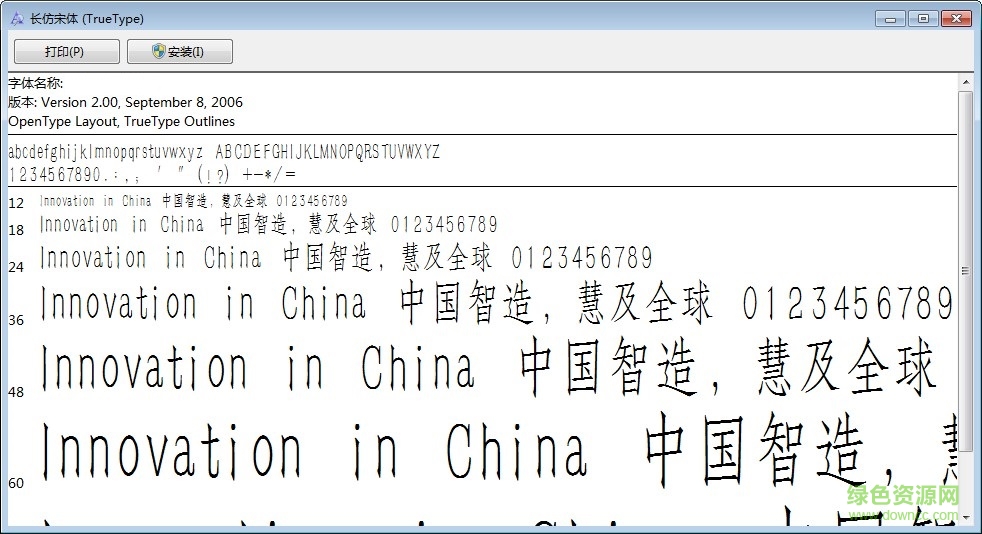
hyswlongfangsong是什么字體?hyswlongfangsong字體是一款漢儀長仿宋體,字形修長,筆調(diào)細秀,清雅有氣質(zhì),結(jié)構(gòu)的嚴謹度較高,適合用在雜志、書籍、影視等領(lǐng)域,需要的朋友快來綠色資源網(wǎng)下載吧!
仿宋是主要的中文字體之一,但是它的使用頻率并沒有宋體、楷體高,而其實我們在電腦上面看到的仿宋是字體設(shè)計者根據(jù)古籍作品加工的,刪去了一些細節(jié),使得字體更加平滑,但是卻失去了一些字體原型的風(fēng)韻。